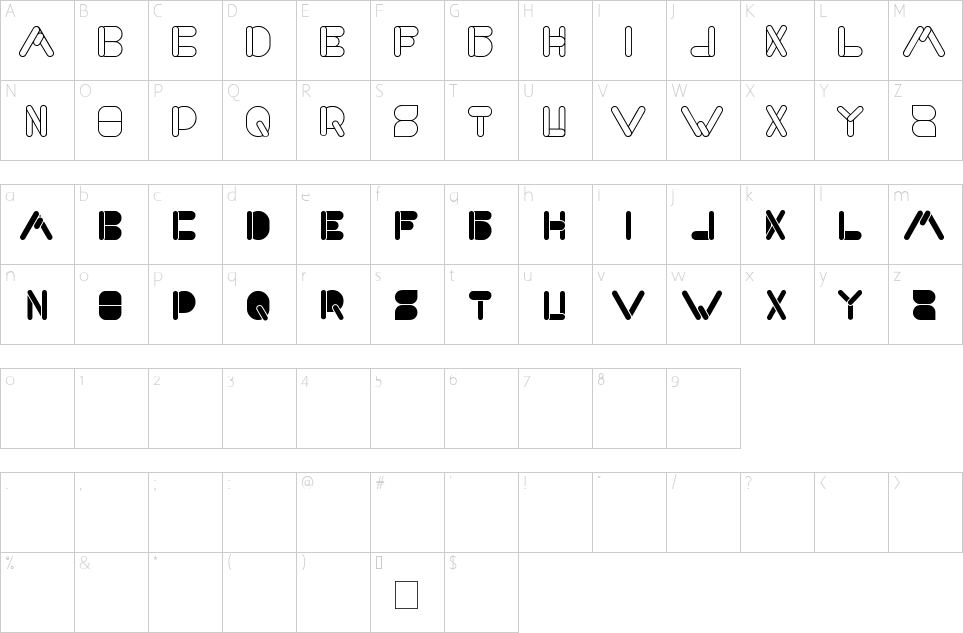
Descubra a fonte ideal para seus projetos digitais com o Maximum Kilometer font, uma fonte grátis disponível tanto para Windows quanto para Mac. Desenvolvida por um designer desconhecido, esta fonte se destaca pelo seu estilo atraente e semelhante ao imposto de kilometragem. Se você está procurando por uma fonte moderna e versátil, a Maximum Kilometer font é uma excelente escolha. Com apenas 2,854 downloads, já é um sucesso na comunidade de fontes gratuitas. Sua simplicidade e modernidade tornam a Maximum Kilometer font um recurso valioso para designers de todo o mundo. Não deixe de explorar essa fonte única e útil que pode transformar seu próximo projeto digital.